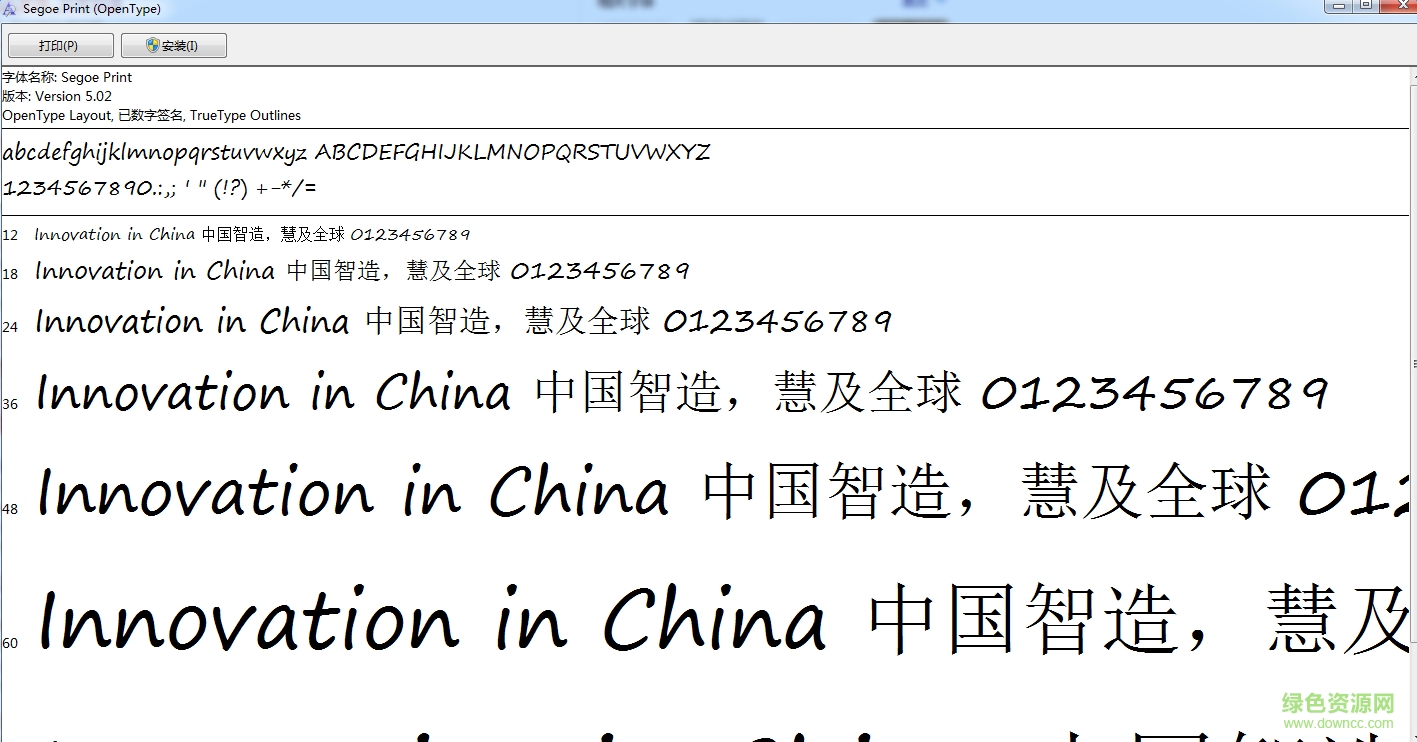
segoe print粗體(西方)
segoe print是什么字體?segoe print字體是一款好看的西方字體,字形清秀,線條從容,效果出色,喜歡這款字體的朋友歡迎在綠色資源網(wǎng)下載!
手寫體介紹
手寫體是一種使用硬筆或者軟筆純手工寫出的文字,手寫體文字代表了中國(guó)漢字文化的精髓。這種手寫體文字,大小不一、形態(tài)各異,在計(jì)算機(jī)字庫(kù)中很難實(shí)現(xiàn)錯(cuò)落有致的效果。只能使用手工寫字的方法傳承下去。
segoe print字體筆畫隨意,形態(tài)自然,有點(diǎn)像英文手寫體,不像其他電腦字體一樣嚴(yán)謹(jǐn)和格式化,帶有一絲人情味,可應(yīng)用于美術(shù)設(shè)計(jì)或網(wǎng)頁(yè)制作方面!